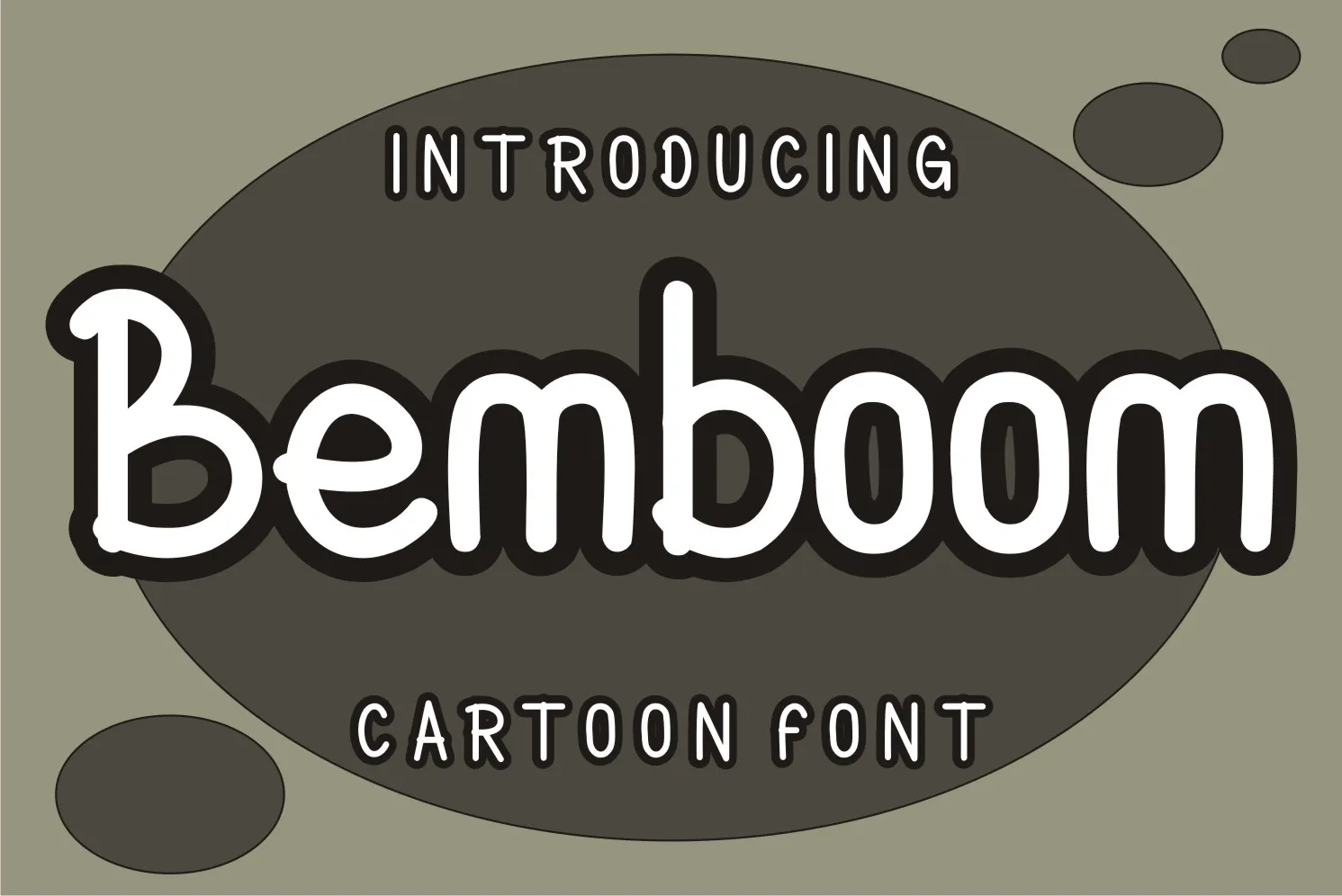
Bemboom Font – Download Grátis
Esta fonte decorative é a escolha perfeita para aqueles que buscam uma aparição relajada em suas criações digitais. Desenhada pelo designer letterfiastudio, ela traz um estilo informal e uma vibe casual ideal para momentos onde você quer transmitir uma sensação leve e despreocupada. Seja para gráficos de web, design gráfico ou até mesmo mensagens personalizadas no WhatsApp, a Bemboom Font é sempre uma escolha segura para dar ao seu projeto aquele toque especial que precisa. É perfeita para quando você quer manter tudo simples e descontraído, sem perder o estilo que sua mensagem merece. Não hesite em explorar suas possibilidades com esta fonte versátil que combina simplicidade e elegância.
Designer: letterfiastudio